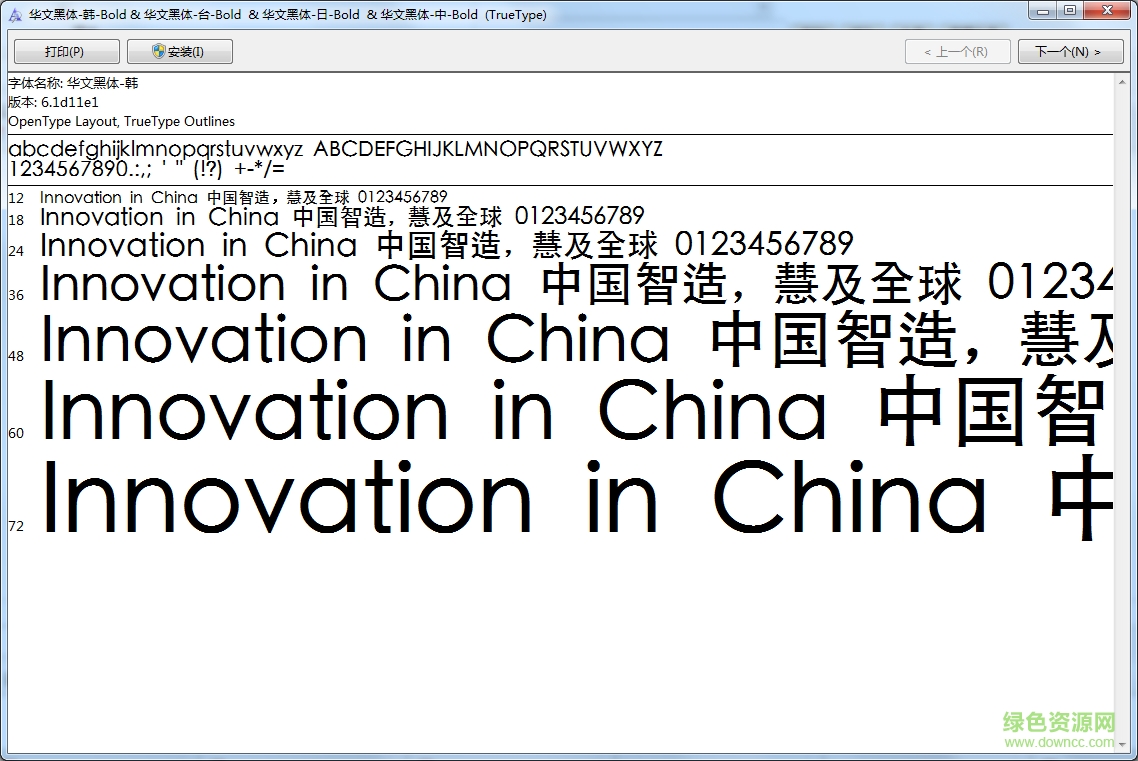
黑體bold字體是一款加粗版的黑體字體,字體的線條筆畫整齊又美觀,常見于書面報(bào)告,用在排版、印刷等方面效果非常棒,喜歡的朋友快來下載吧!
在中文中,沒有襯線的字體通常稱為黑體,這時(shí)這個(gè)詞的范疇和無襯線字體(Sans-serif,亦稱無腳字)是類似的。所以在中文字體中常用“黑體”,在西文中常用“無襯線體”的稱呼。
黑體字在字架上吸收了宋體字結(jié)構(gòu)嚴(yán)謹(jǐn)?shù)膬?yōu)點(diǎn),在筆畫的形狀上把橫畫加粗且把宋體字的聳肩角削平為等線狀,形成橫豎筆畫粗細(xì)一致,變宋體字的尖頭細(xì)尾和頭尾粗細(xì)不一的筆畫為方形筆畫。